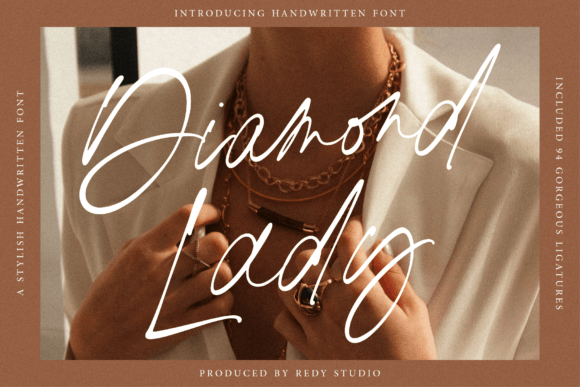
Diamond Lady
Diamond Ladyのような高品質の素材をお探しの場合、このプレミアムパッケージはクリエイティブなプロジェクトに素晴らしい選択です。
精密に作られたDiamond Ladyは、クリーンなベクター、滑らかなタイポグラフィ、そして安心のための商用ライセンスを提供します。
POD(オンデマンド印刷)製品、結婚式の招待状、またはソーシャルメディアのグラフィックを作成している場合でも、Diamond Ladyは理想的です。